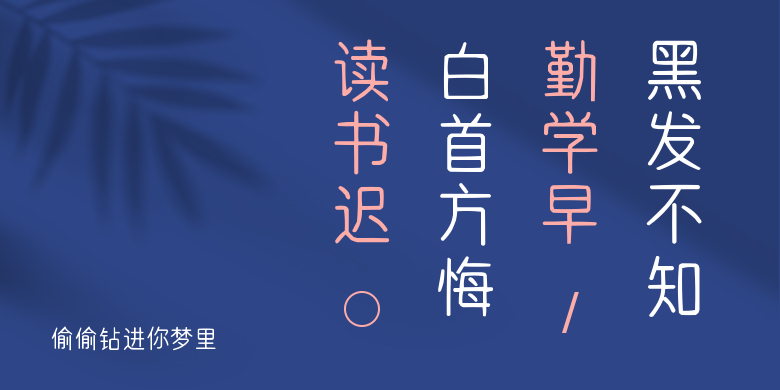
偷偷钻进你梦里,这款字体结构工整、笔画清晰,兼顾美观与易读性,适用于标题、正文、海报、包装、LOGO 等多种场景。字形优雅稳定,风格百搭耐看,适配日常排版与创意设计,让文字呈现更舒适、更具质感。偷偷钻进你梦里一笔一画,皆是细节,以均衡的比例、流畅的线条打造舒适视觉体验,字形端正大气,风格简约现代。无论是商业设计、品牌宣传还是日常排版,都能轻松驾驭,让文字更有格调与力量。偷偷钻进你梦里字体下载。